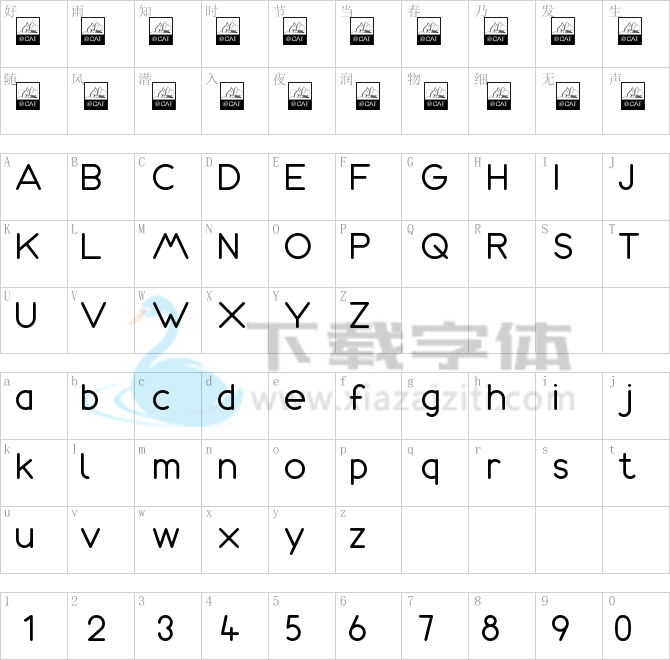
Amazonas.ttf字体下载,这款字体结构工整、笔画清晰,兼顾美观与易读性,适用于标题、正文、海报、包装、LOGO 等多种场景。字形优雅稳定,风格百搭耐看,适配日常排版与创意设计,让文字呈现更舒适、更具质感。Amazonas.ttf字体下载一笔一画,皆是细节,以均衡的比例、流畅的线条打造舒适视觉体验,字形端正大气,风格简约现代。无论是商业设计、品牌宣传还是日常排版,都能轻松驾驭,让文字更有格调与力量。Amazonas.ttf字体下载字体下载。
Amazonas.ttf图片展示
• 字体名称:Amazonas
• 字体全名:Amazonas
• Postscript:Amazonas